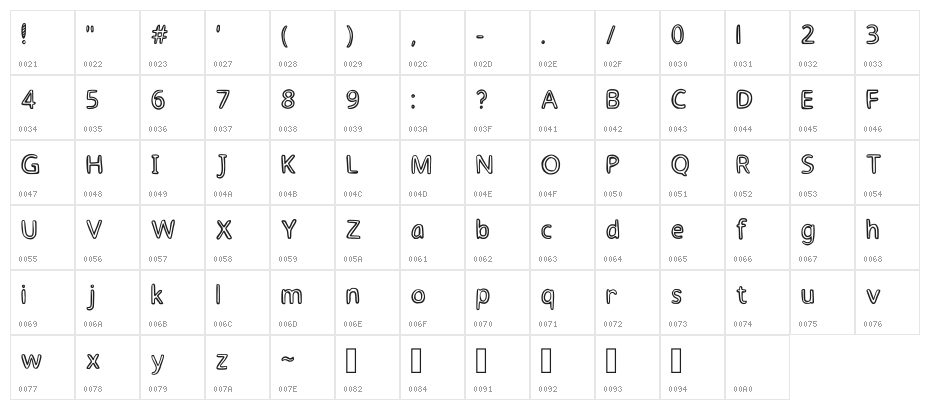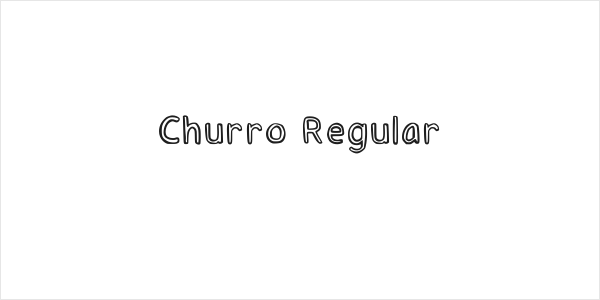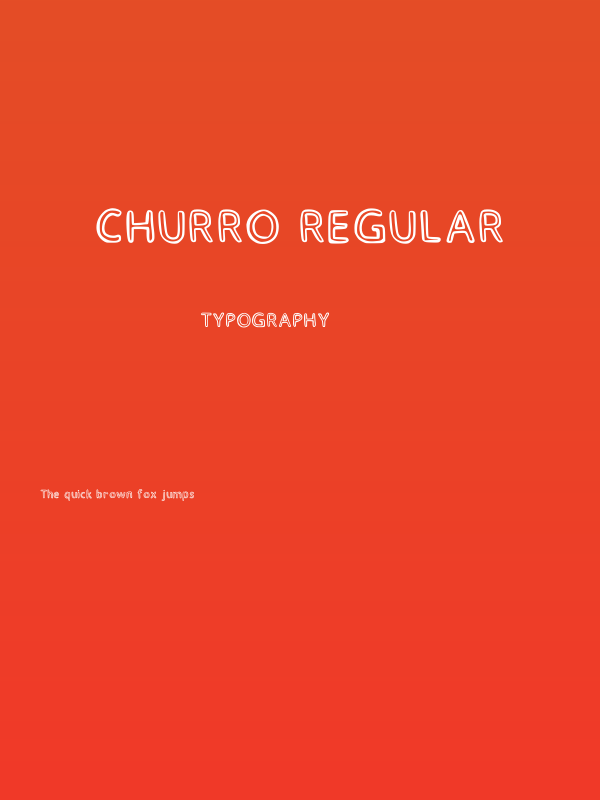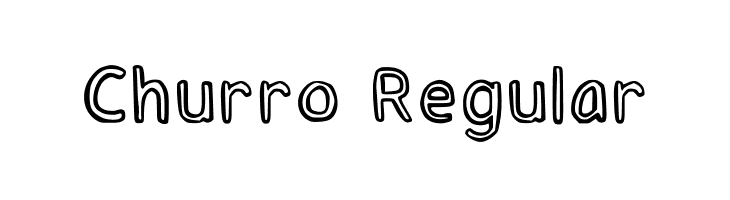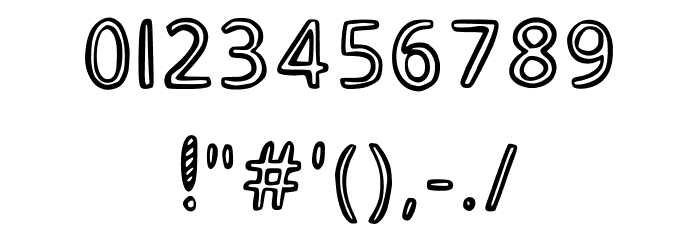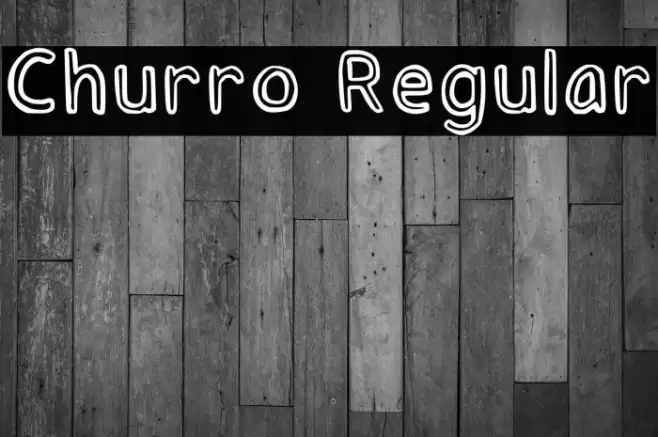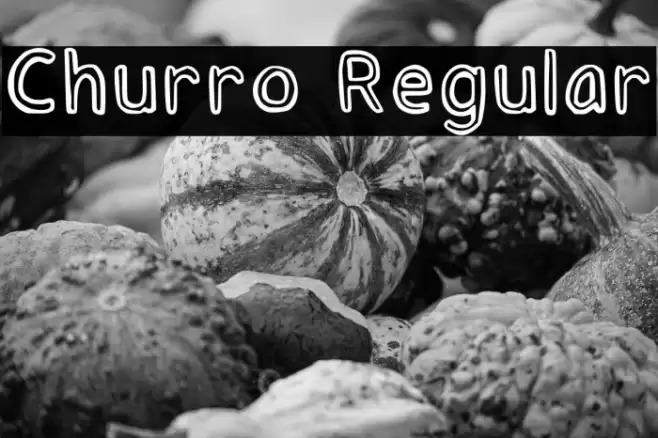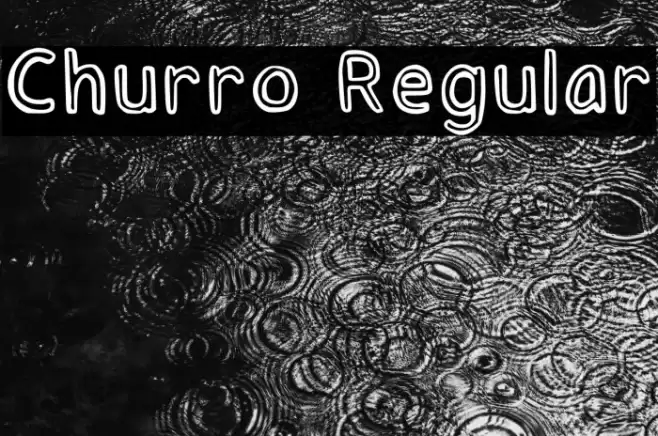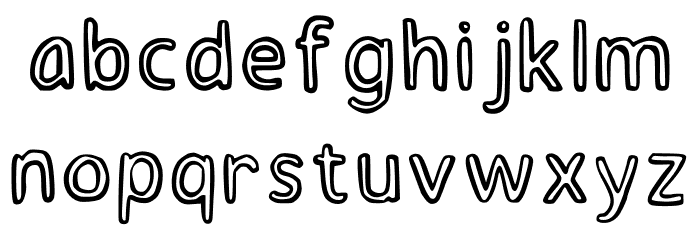
Churro Regular Font
✎ Cartoon
Fonts by charlotte Lee
| 名前 | Churro Regular |
| フォントファミリー | Churro |
| Style | Churro-Regular |
| カテゴリ | Cartoon |
| 全体的なスタイル | Whimsical |
| おすすめプロジェクト | Ideal for children's books, playful branding, party invitations, and creative posters. |
| 作者 | Fonts by charlotte Lee |